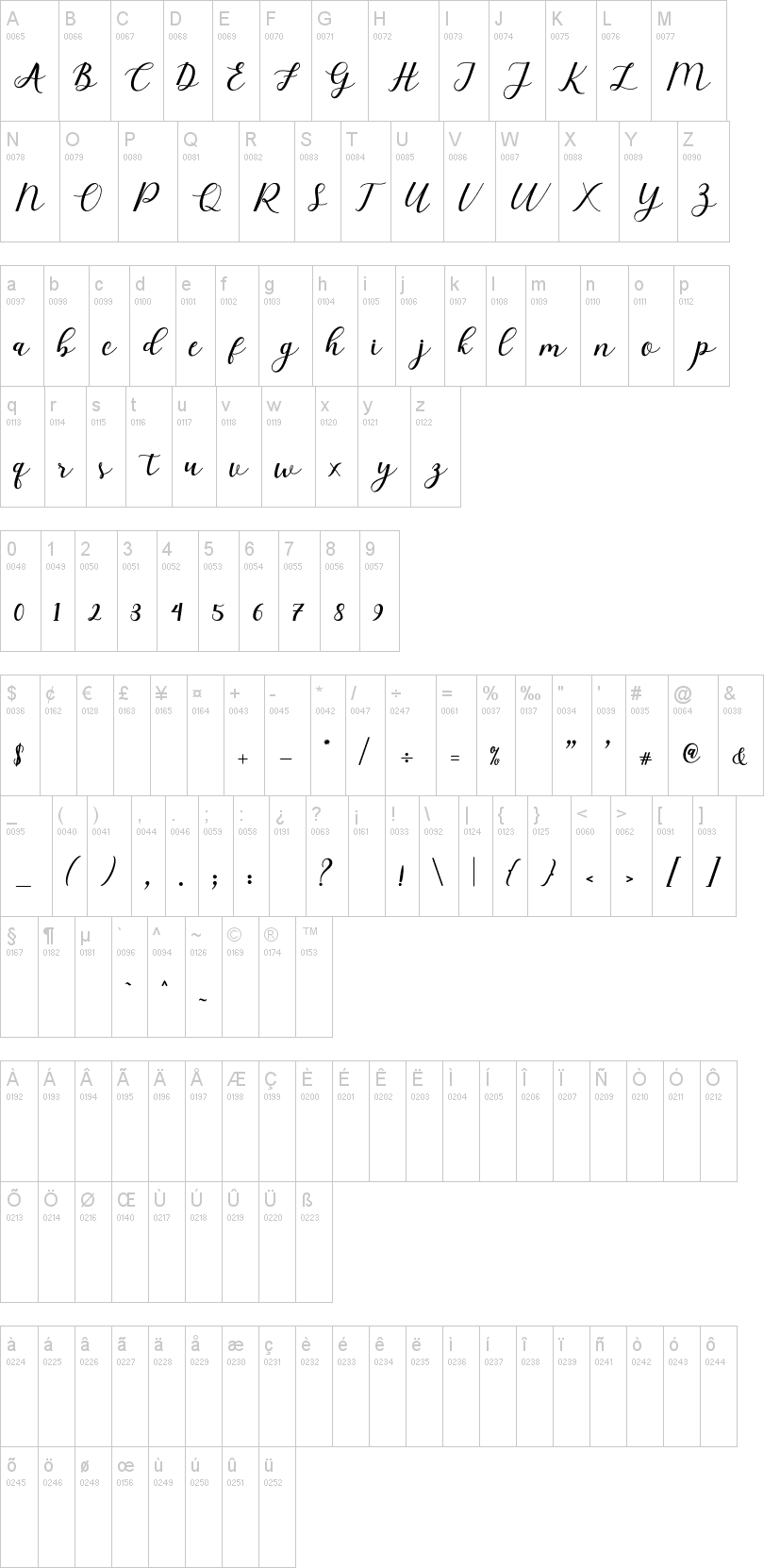
Elizabeth Script
Elizabeth Script (伊丽莎白手写体) 是一种优美、典雅的手写字体,具有浪漫和优雅的风格。它是由 font designer Casady Greene 创造的,可以用于多种设计项目。 Elizabeth Script 字体的特点包括: 1. 独特的手写风格:字母间距离适中,字母笔画流畅,线条柔和而有力。 2. 多种字体样式:此字体包含多种字体手写样式,包括粗体、斜体、等宽体等,可满足多种设计需求。 3. 多语言支持:它支持多种语言,包括英语、法语、德语、西班牙语、意大利语等等。 Elizabeth Script 字体适用于多种设计场景,包括婚礼、品牌、印刷品、海报、标志等等。它的优美和典雅的特点,使其在各种设计中特别受欢迎。
Elizabeth Script是一款非常不错的手写艺术字体,具有很好的视觉感,适合于文化类的宣传设计、商业类品牌的广告和产品包装设计以及个性化文字排版等较多场景。